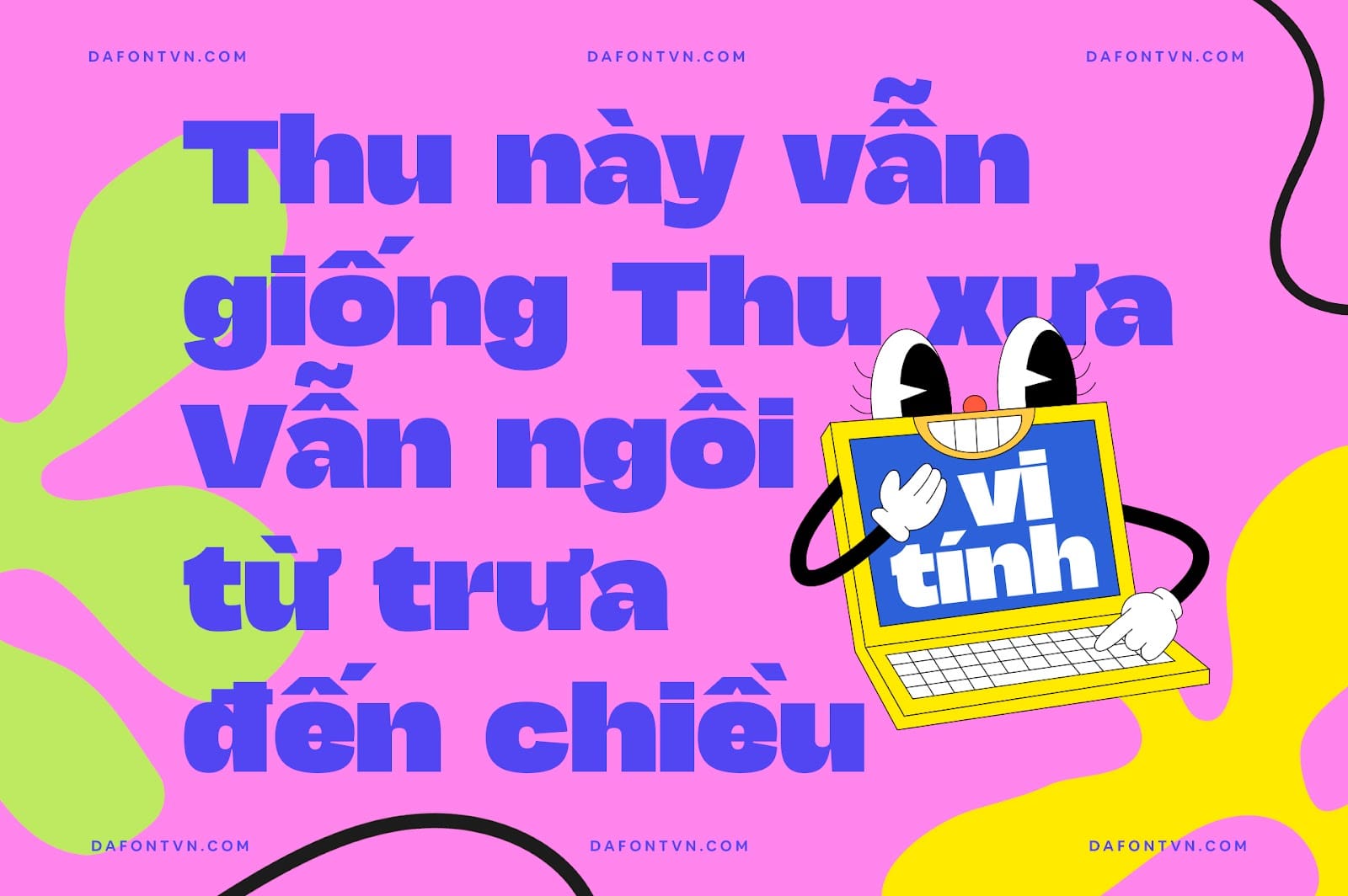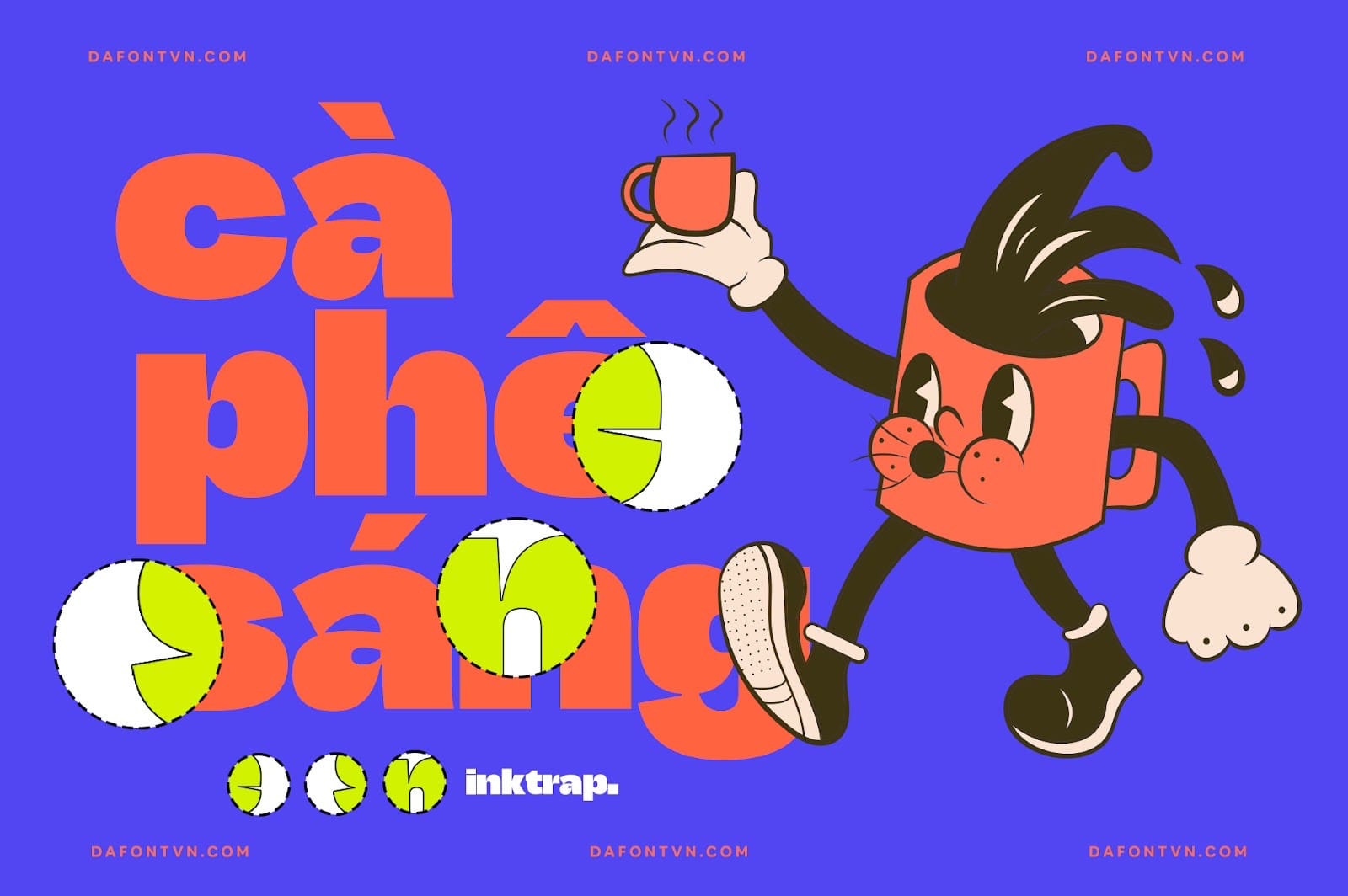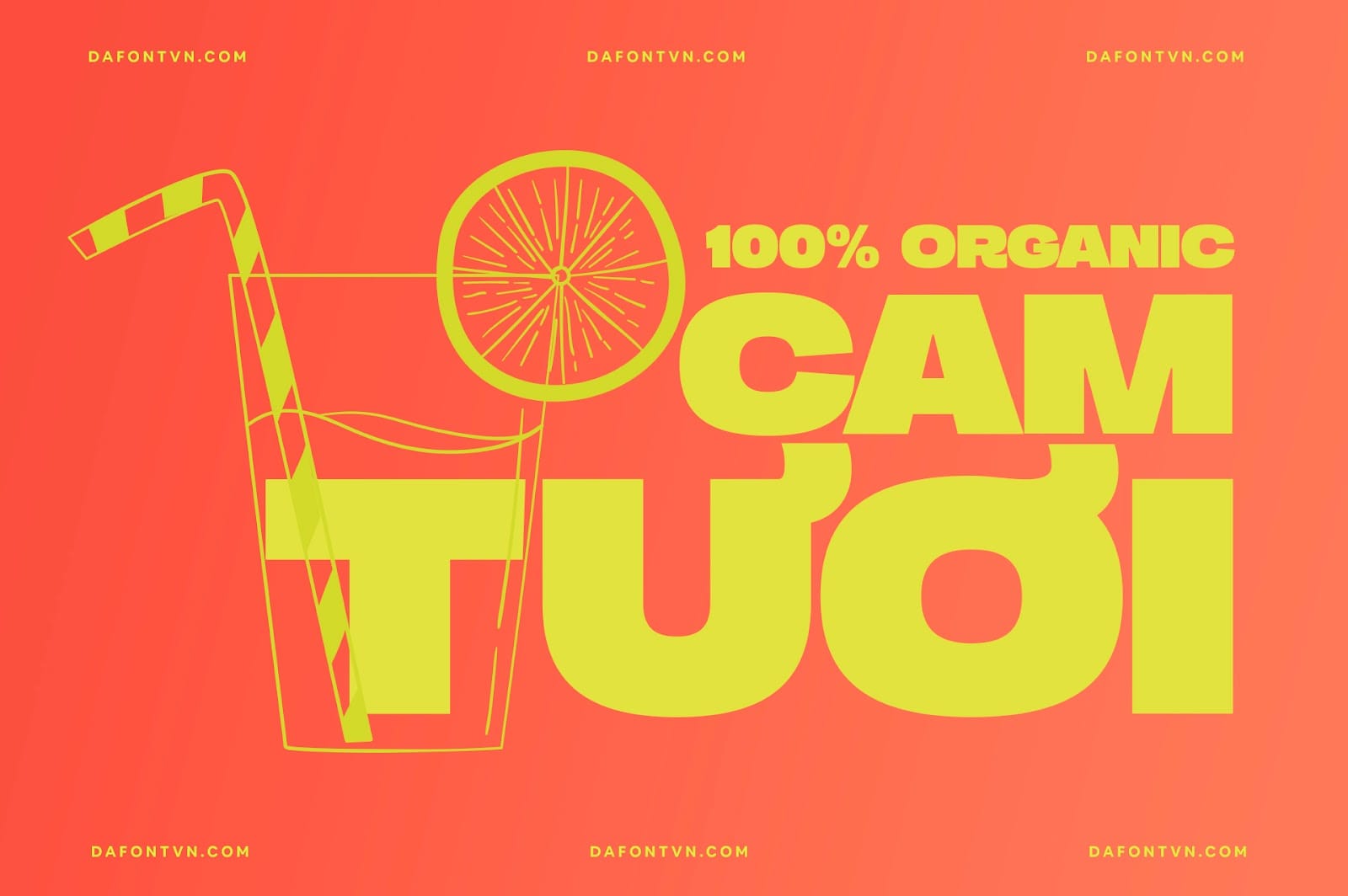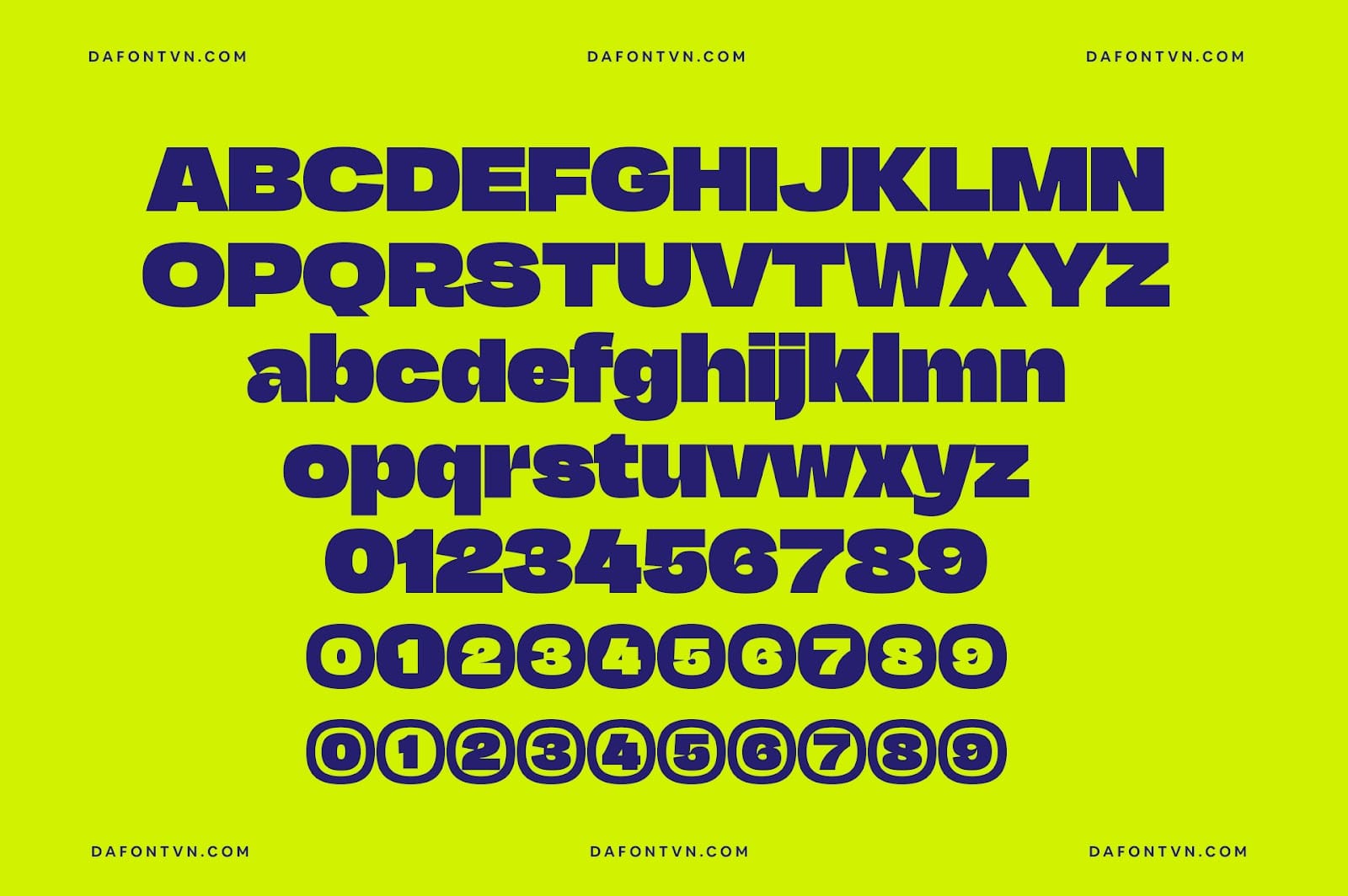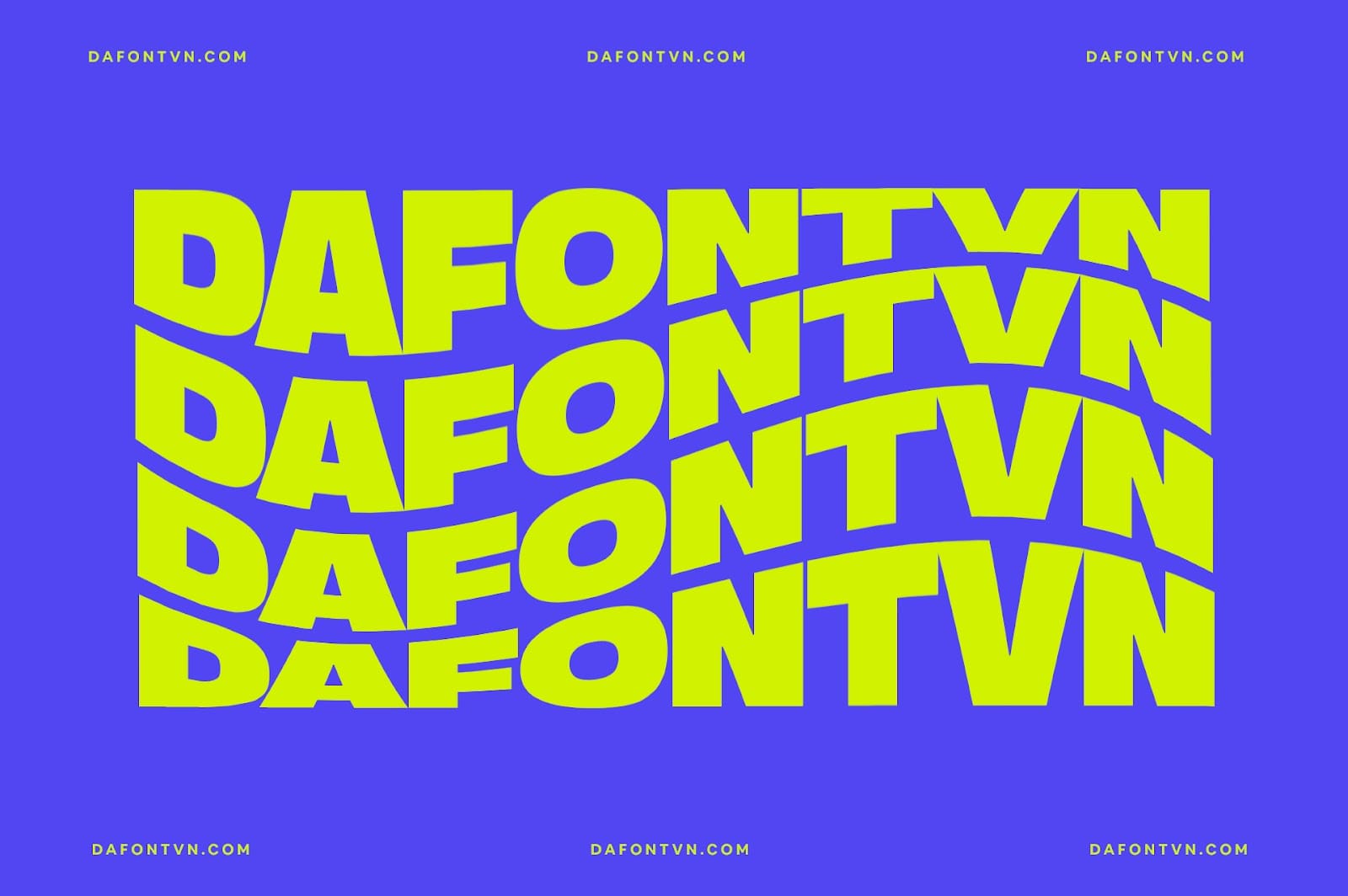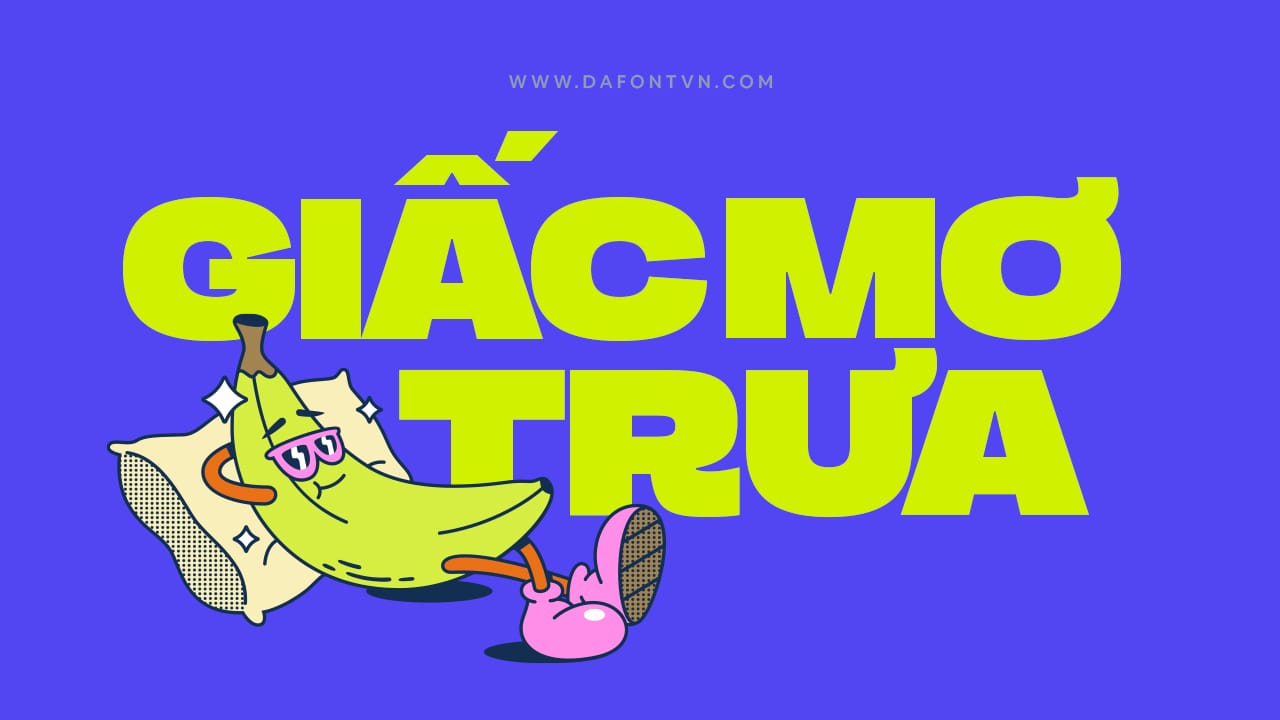
Constructio Grotesk là một phông chữ sans serif có phần thân cực đậm nhưng vẫn có độ tương phản cao. Phông chữ này rất độc đáo vì nó có một số glyph có cấu trúc sẵn có, đó là các ký tự G, S, a, e, g và s. Ngoài ra còn có một số glyph khác trên chữ số và dấu câu.
Phông chữ này rất đẹp khi kết hợp với màu sắc thiết kế tương phản. Constructio Grotesk phù hợp để sử dụng làm tiêu đề và hiển thị tốt ở kích thước lớn bạn có thể sử dụng font chữ này làm bìa sách, logo, poster, quảng cáo, bao bì sản phẩm….
Ngoài ra font chữ có các tính năng: SS01, SS02, phân số, chỉ số trên và chỉ số dưới.